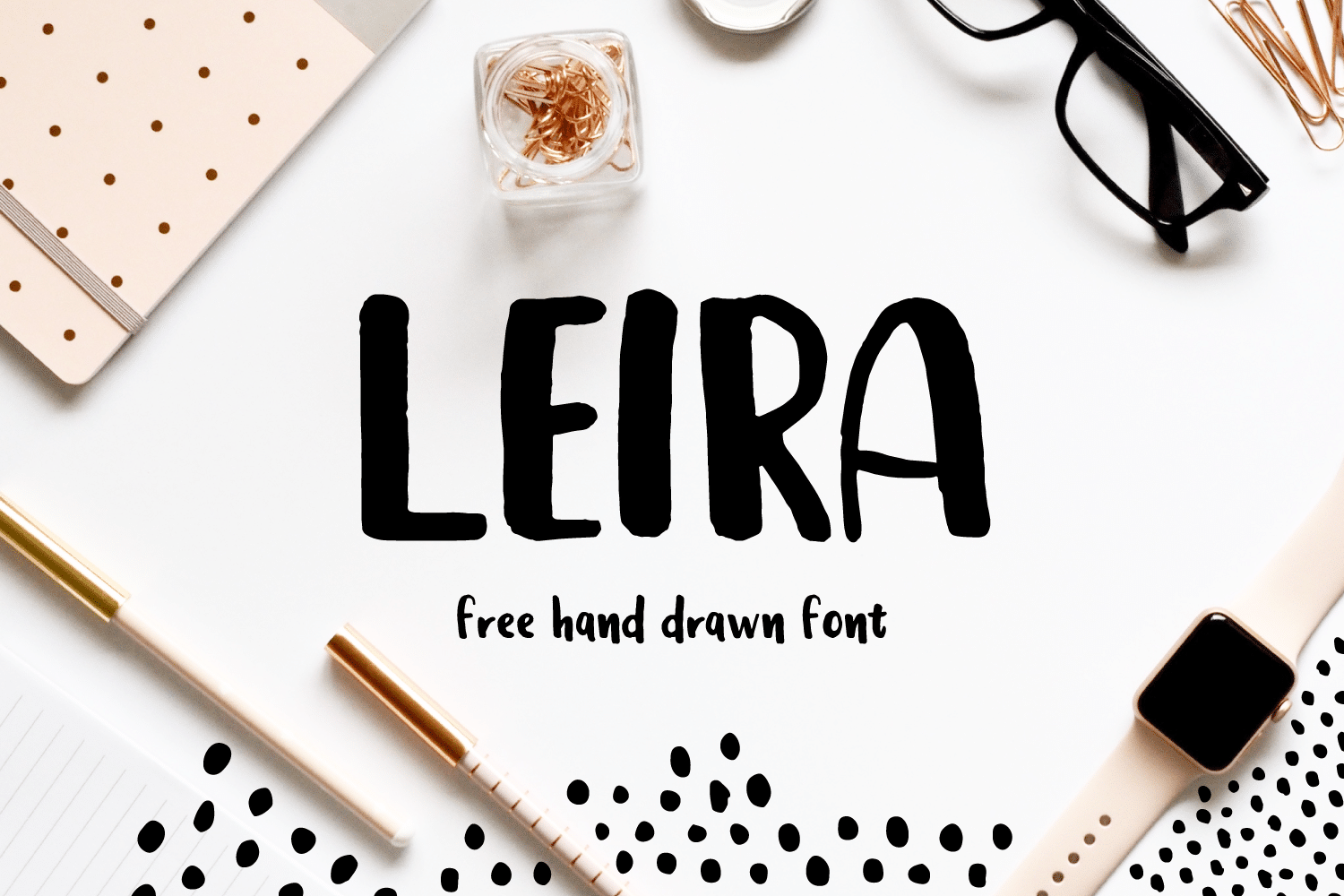
Leira ist eine handgezeichnete Pinselschrift – mit markanten Details, auffällig und gut lesbar. Es ist ideal für die Erstellung von Identitäten, Schlagzeilen, Logos, Plakaten, Karten, Verpackungsdesign usw. – im Grunde überall wo man etwas Auffälliges mit einem charmanten, handgemachten Touch in Szene setzen will.